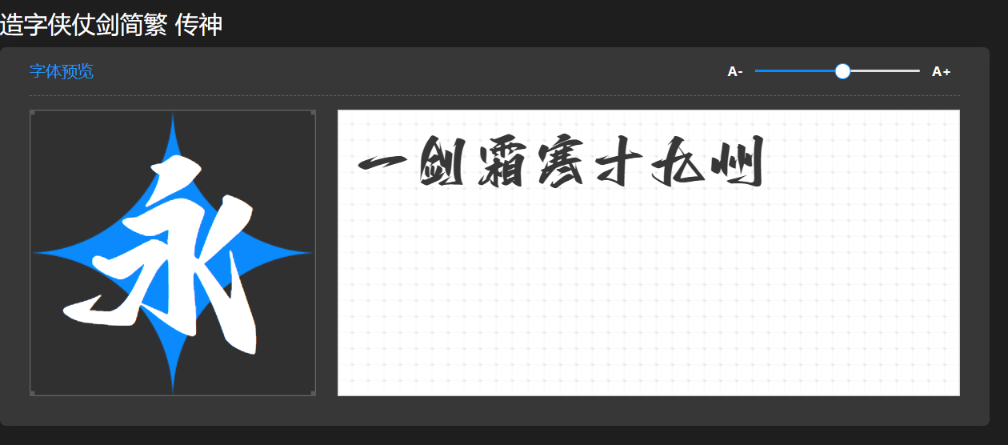
快意江湖,侠气纵横 | 造字侠仗剑简繁——一款潇洒张扬的国风书法字体
中国人的江湖在哪?以前是刀光剑影、快意恩仇的人间,现在的江湖,是生活。跟生活息息相关的都是品牌的江湖必争之地。伴随国潮崛起,国人的文化认同及文化自信,国潮已然成为各品牌的营销之王。
励字造梦共创字库推出的独步江湖的国潮书法字体——造字侠仗剑简繁 传神,一款字形稳重、笔画张扬的书法字体。折、提、钩等部首干净利落、高度折叠,颇有豪侠仗剑江湖的潇洒之感。